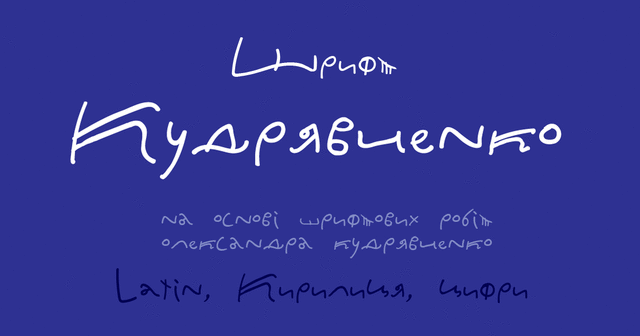
Шрифт Kudriavchenko разработан специально для украинских текстов, но латиница в нем тоже есть. Это веселый и позитивный шрифт, который относит нас к временам Киевской Руси, напоминая старинные граффити на стенах храмов. Основным вдохновением послужил почерк украинского художника Александра Кудрявченко, которым оформлено большинство его работ. Шрифт разработала Ирина Кудрявченко в 2019 году.
Ассоциации c семейством KudriavchenkoКачества и характер:
домашний, бытовой, ручной, кустарный, самодельный, ремесленный, неотесанный, неровный, веселый, задорный, смешной, странный, дружелюбный, добродушный, добрый, радостный, прыгающий, игривый, приветливый, озорной, непоседливый, подвижный, детский, наивный, проволочный, счастливый, натуральный, весенний, органический, причудливый, прикольный, небрежный, посконный, сермяжный, деревенский, крафтовый, колоритный, рукотворный, артизанальный, почвенный, народный, древний, птичий, берестяной, лубочный, неправильный, случайный, лесной, крестьянский, этничный, провинциальный, самобытный, неординарный, бабушкин, сказочный, былинный, зеленый, экологичный, традиционный, староверский, языческий, милый, мягкий, фермерский, летний, архаичный, симпатичный, племенной, природный, эмоциональный, темпераментный, чувственный, вдохновенный, поэтический, лирический, лихой, неряшливый, быстрый, динамичный, свободный, оригинальный, артистичный, характерный, живой, страстный, творческий, проворный, вернакулярный, неформальный, бегущий, мультяшный, ламповый, теплый, дикий
детская книжка, карандаши, юмор, анимация, мультфильм, трава, весна, хэллоуин, развлечения, жуки, пауки, насекомые, заклинание, монастырь, хлеб, этнография, фольклор, лубок, сказка, целитель, травник, знахарь, природа, хенд мейд, пословица, частушка, прибаутка, байка, сказание, предание, зелье, животные, хюгге, живопись, игрушка, игра, отдых, мягкая игрушка, лето Стилистика: